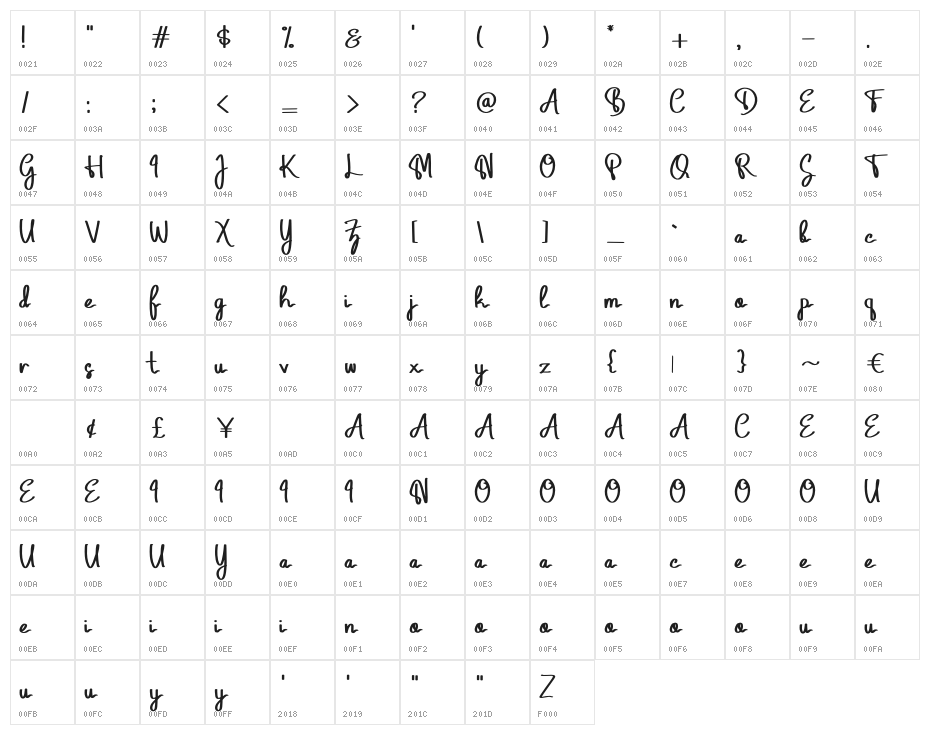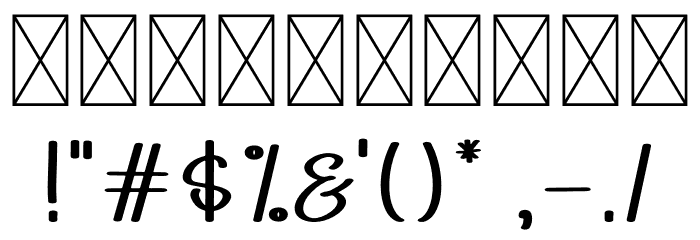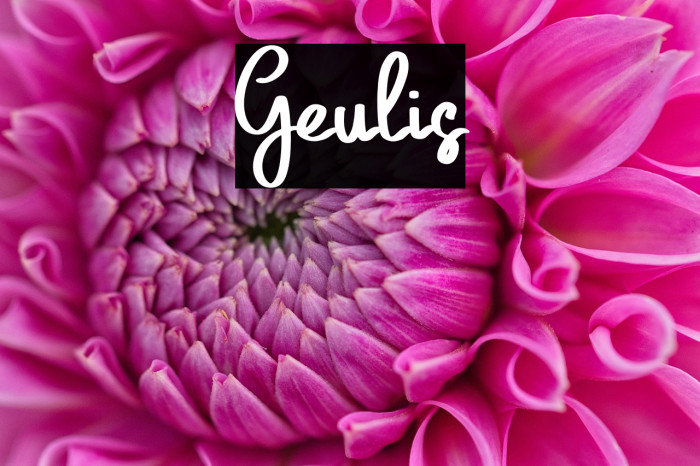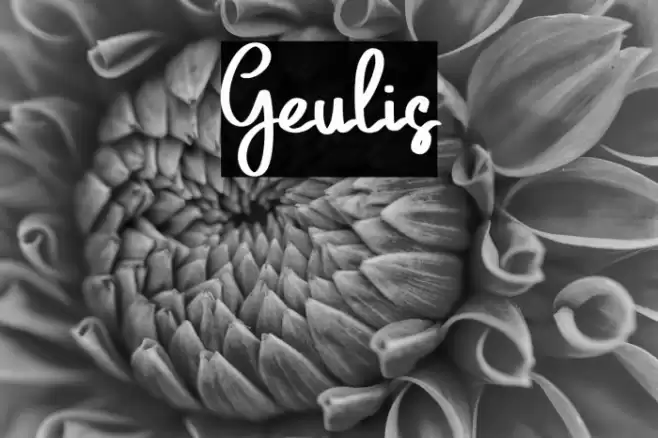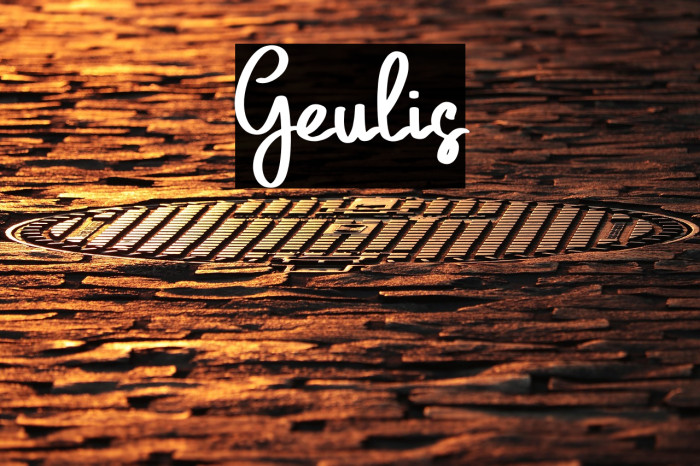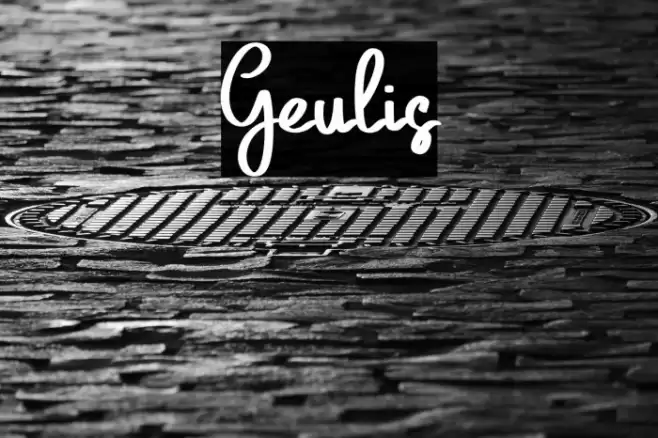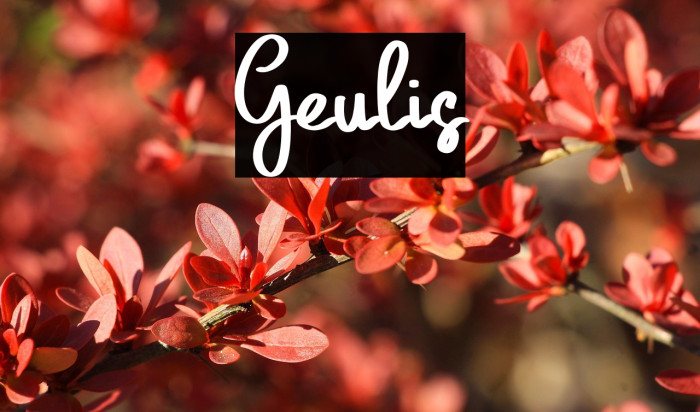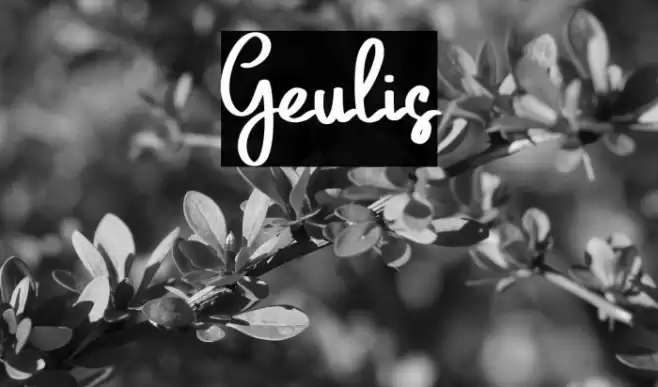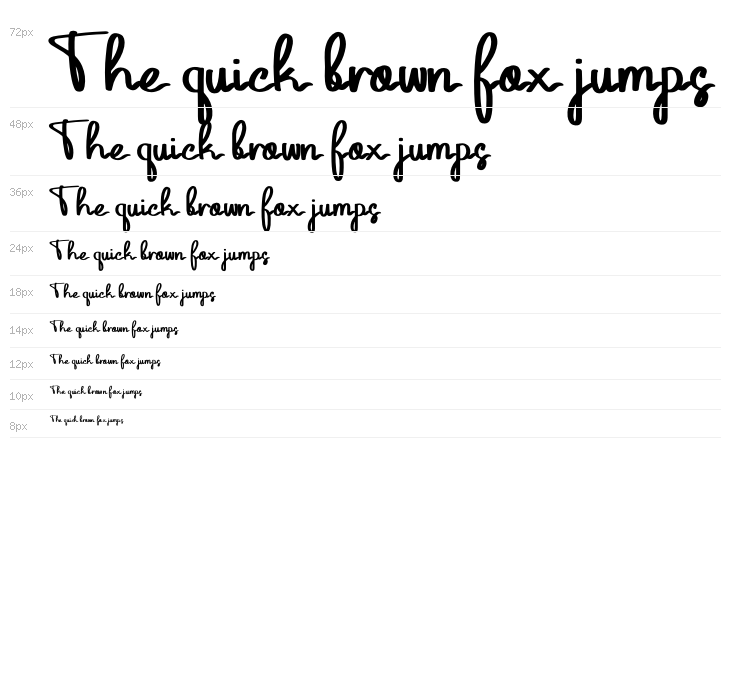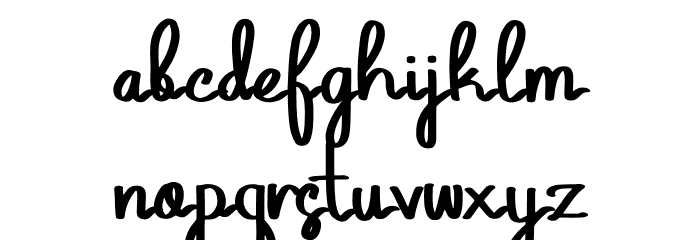
Geulis Font
| Область применения | Logos, Headlines, Invitations |
| Рекомендуемые проекты | Ideal for wedding invitations, greeting cards, branding, and creative social media graphics. |